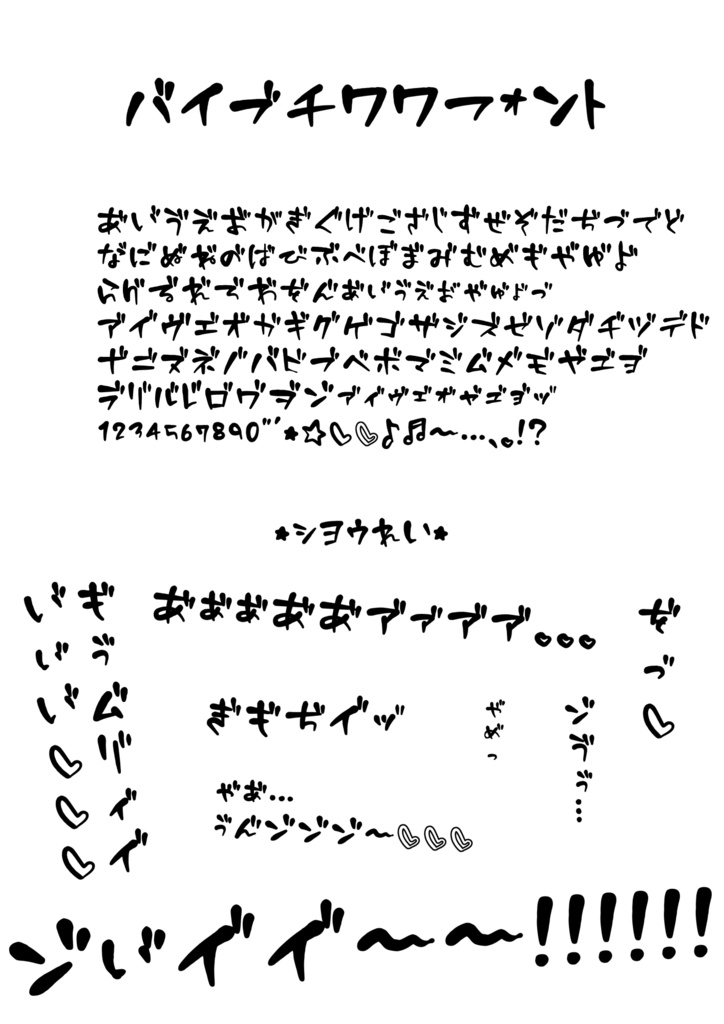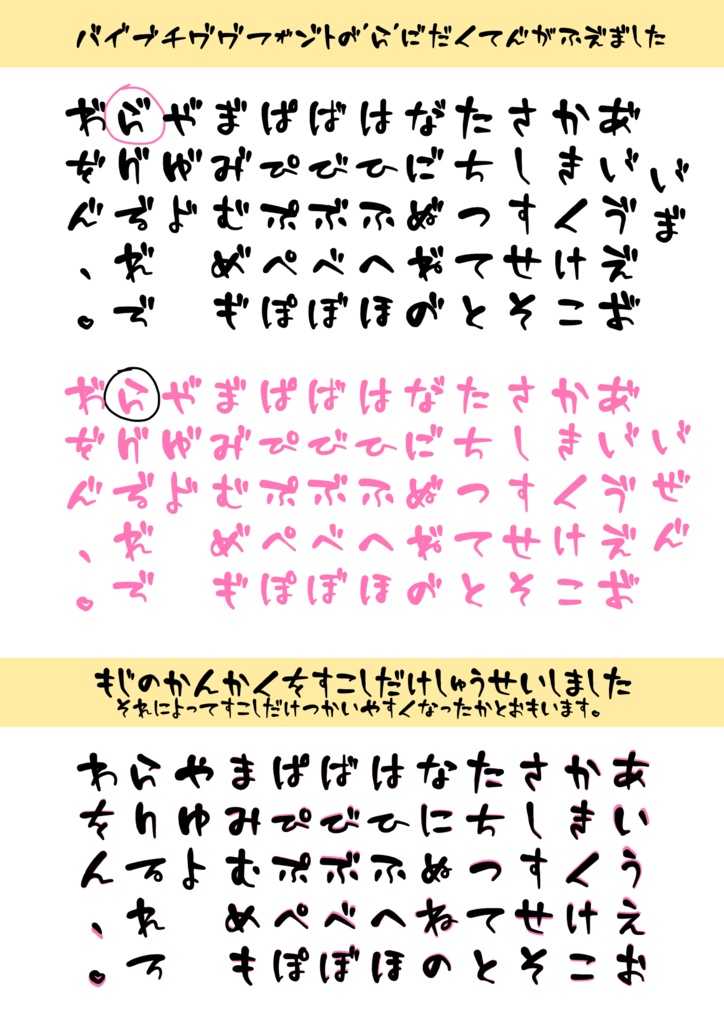
汚喘ぎフォント
「読めないわけじゃないけれども汚い」 と友人に笑われる自分の文字を活かしたフォントです。 エッチな場面などのオノマトペや汚喘ぎにちょうど良いと 言われましたのでよろしければみなさまもどうぞ。 通常のひらがな・カタカナの五十音と、数字などの文字を収録した "チワワフォント"と、異様に濁点がついた"バイブチワワフォント" の2種と、その2種を纏めた"汚喘ぎチワワセット"を用意しています。 ※汚喘ぎチワワセットの内容はチワワフォントとバイブチワワフォントと同じです 利用規約等が記載されていますので、 同梱の「readme.txt」をよくご覧になってからご利用ください。 ------以下、利用規約の一部抜粋です------ ・クレジット表記や事前連絡、利用報告は必要ありません。 ・商用、個人用に関わらず印刷物・映像作品等へ使用が可能です。 ・全フォントデータの著作権は、製作者のぱょったに帰属します。 【OK】 -Webサイトの画像への文字入れ -動画・映像の文字入れ -PDF、ソフトウェアへの埋め込み、ゲームへの使用 【NG】 -フォントファイルの再配布 -自作発言 -商標登録 ----------------------------------------------- 法人様からのお問い合わせをいただくことが増えてきたため、 簡単ではありますが、利用条件を追加明記させていただきます。 ※※※※※※※※※※※※※※※※ 法人利用をご検討中の方へ ※※※※※※※※※※※※※※※※ 本フォントは、同人・個人利用を主として制作しておりますが、 法人様でのご利用も可能です。 法人利用の場合は、実際にフォントをインストールして 使用するパソコン(端末)1台につき1点のご購入をお願いいたします。 (使用人数ではなく、使用端末数を基準としてください) 購入された数を超える端末へのインストール、 ならびに第三者への再配布はご遠慮ください。 制作物への使用(商業作品・業務利用を含む)は、 通常のフォント利用の範囲内で問題ございません。 法人様向けの特別プランや包括ライセンスは、現時点ではご用意しておりません。 ご不明点がございましたら、BOOTHのDMよりお気軽にお問い合わせください。 ※追記(2025.1.23)※ !アップデートのお知らせ! 2026年2月中にチワワフォントの一部を以下の通りに変更します。 カタカナの小文字の『ッ』についてあった濁点を通常の『ッ』へ切り替えます。 変更に伴いチワワフォントをご利用いただいていた方へはご迷惑をおかけしますが 通常の『ッ』をお使いいただく場合は再度ダウンロードをお願いします。 濁点がついたまま使いたい方➡︎再ダウンロードの必要はありません。 通常と濁点の両方使いたい方➡︎バージョンアップをされているファイル名を 必ず任意の名称に変更した上で旧バージョンへ上書きしない形で 2種類のチワワフォントを登録してご利用ください。 アップデートが完了しましたらこちらの追記欄にて再度お知らせいたします。 ========= 一部変更のお知らせ ========= 1.汚喘ぎチワワセットの中身を含めた バイブチワワフォントの『ら』を濁点付きに変更しました。 2.少しだけ文字の間隔を見やすく修正しました。 3.それぞれのフォントにotfとttfの2バージョンを用意しました。 既にご購入済みの場合は お手数ですが必要な方は再度ダウンロードをお願いします。 (追加料金はかかりません) ※追記(2025.7.7)※ ============== 価格改定のお知らせ ============== 2025年9月1日より以下の通りに価格を変更させていいただきます。 チワワフォント :(変更前)150円➡︎(変更後)250円 バイブチワワフォント:(変更前)150円➡︎(変更後)250円 汚喘ぎチワワセット :(変更前)300円➡︎(変更後)500円 いつもBOOSTやわざわざ同じ内容をまとめ買いしていただく等 本当にありがとうございます。お心遣い感謝しています。 この度、最近気を使っていただく事が増えたため上記のお手数を減らす目的も含め元々の値段を変更させていただく決断をしました。 低価格でお試しのように気軽に使えてみなさんの創作物のお手伝いになれればとの考えは変わらずですので今後しばらくは改定後の値段からの変更は考えていません。 少しでもお安くと言う方には申し訳ありませんが8月中にご検討いただければと思います。 ♦︎ データをWindowsで解凍した際に起きてしまう文字化け問題を解消すべく Windowsでご利用の方にも文字化けの問題が起こらないデータを用意しました。 それでも万が一文字化けが起こってしまった場合は以下の内容を参考にしてください。 ※追記(2024.2.6)※ ========== 良くある質問 ========== Windowsをお使いの方から文字化けをする、ファイルが開けずうまく登録できない、フォルダ内にファイルが確認できないとのお問い合わせを度々いただきます。 こちらのデータはMacで制作している為、互換性の問題でWindowsで解凍をした場合に文字化けが生じることがあるようです。 また、Macの圧縮データをWindowsで解凍した中には__MACOSXというフォルダがあり、こちらを開いてデータがない、ファイルが開けない等が起きているようです。 Windowsをご利用のかたで上記のような場合対策は以下の通りです。 __MACOSXというフォルダ内のデータは正しいフォントデータではありません。こちらで開こうとすると「有効なフォントファイルではありません」と表示されてしまいます。 __MACOSXというフォルダ内のファイルではなく、正規のファイルの方を 『(任意のファイル名).otf』と名称変更をしてからご利用ください。 こちらの方法でWindowsでも問題なく使用できたとの確認をしていただいております。 お手数ですがWindowsの方は上記方法をお試しください。